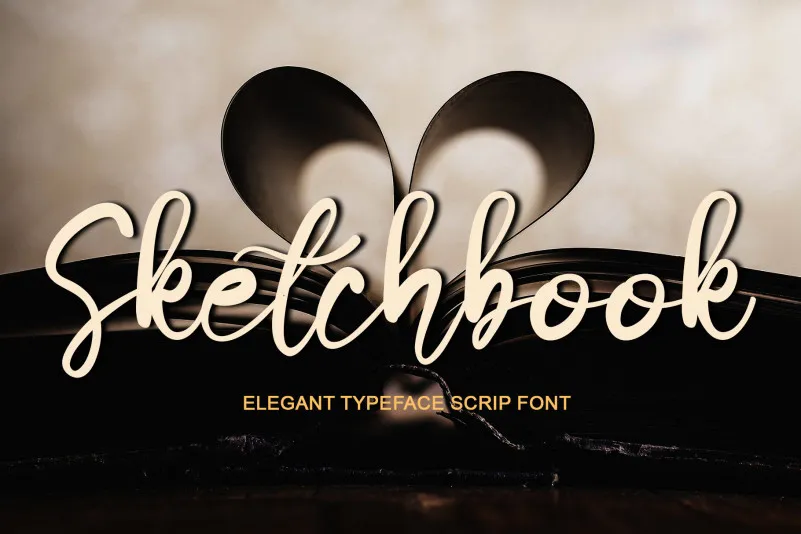
Sketchbook Script Font – Fonte Grátis
Sketchbook Script Font
Esta é uma fonte escrita a mão com traços delicados e finos. Suave e feliz, essa fonte será perfeita para escrever cartões de casamento, convites ou qualquer outro projeto que precise de um toque romântico e personalizado! Adaptada à natureza brasileira, ela traz uma atmosfera encantadora com seus traços delicados, combinando perfeitamente com a essência do nosso país. Sempre procurando inovar no design gráfico brasileiro, esta fonte é um dos recursos indispensáveis para quem busca expressar seu estilo único em projetos digitais ou impressos.